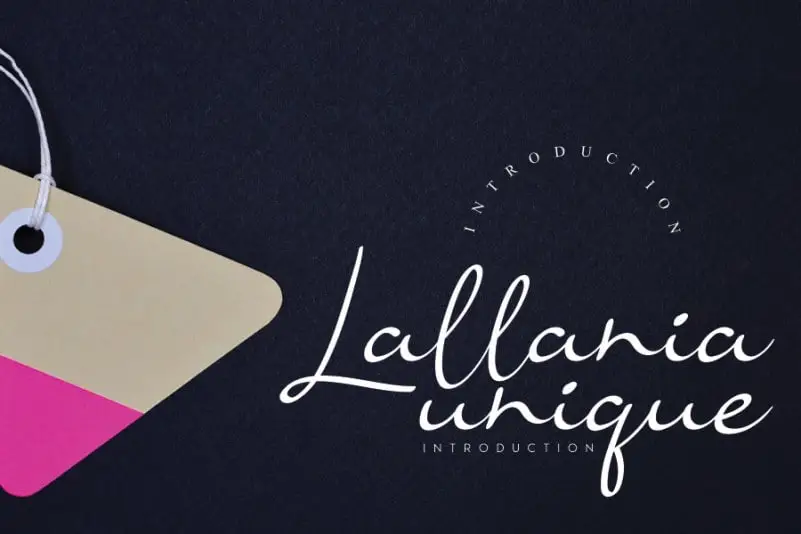
Lallania Handwritten Font – Download Grátis
A Lallania Handwritten Font é uma elegante fonte escrita a mão com um estilo único e fluído, criada para transmitir uma sensação inigualável de tempolessness. Suas linhas são levemente relaxadas e sofisticadas, o que a torna ideal tanto para ambientes formais quanto não-formais de design gráfico. Adaptada à elegância do estilo da calligrafia, esta fonte é perfeita para criações que buscam um toque pessoal sem comprometer a estética. É uma escolha versátil e moderna para designers profissionais que desejam incorporar um ar de sofisticação natural em suas projetos. Ideal tanto para o design editorial quanto para os trabalhos de arte digital, a Lallania Handwritten Font é uma fonte escrita a mão que reflete o espírito do novo milênio ao manter intactas as características únicas da calligrafia tradicional. Seja em banners, nomes de empresas, ou qualquer outro tipo de design gráfico, este é um recurso visual incrivelmente envolvente para os designers profissionais.